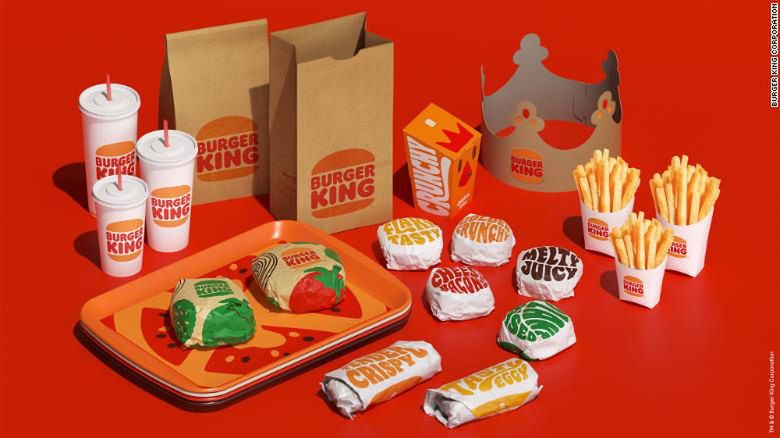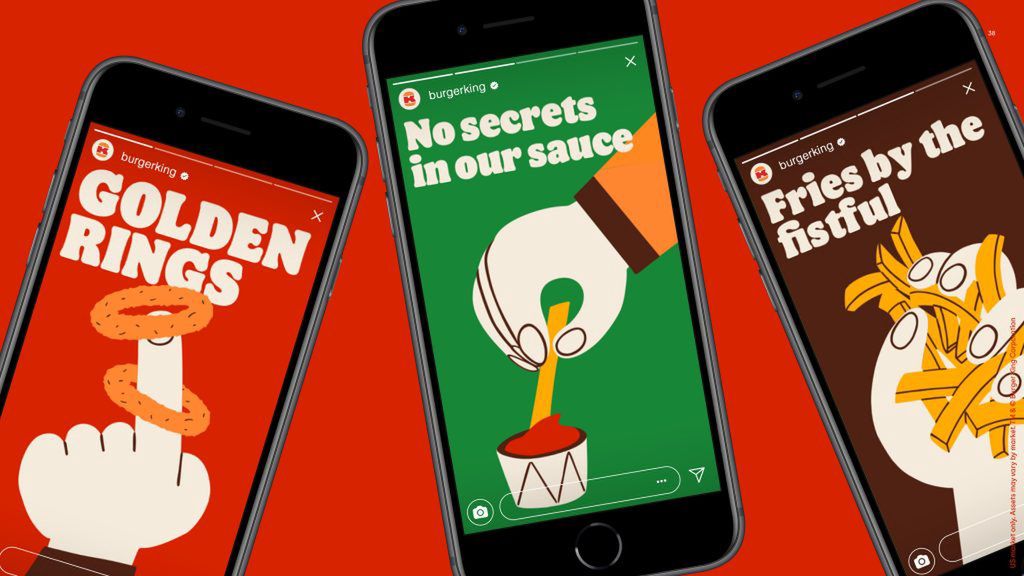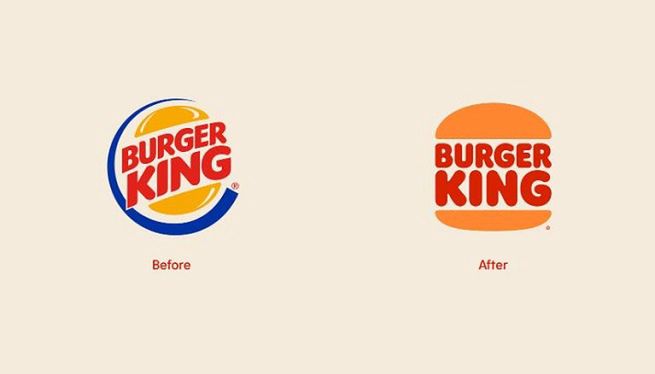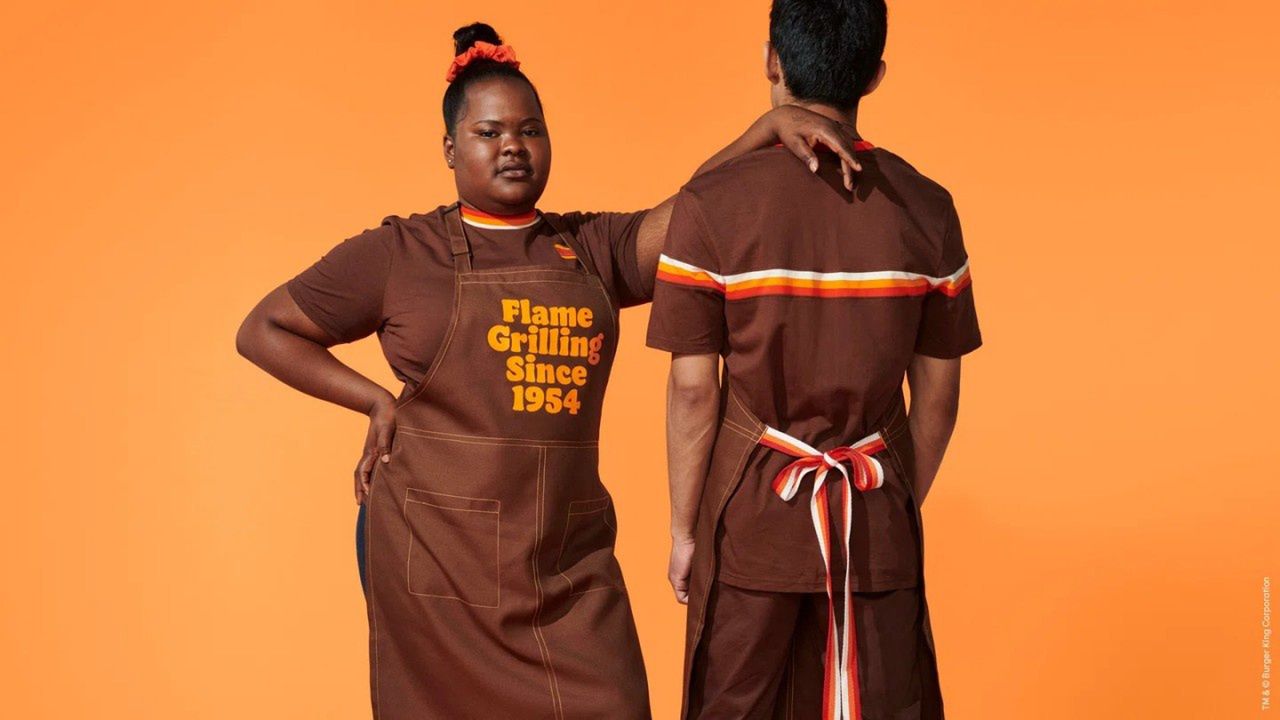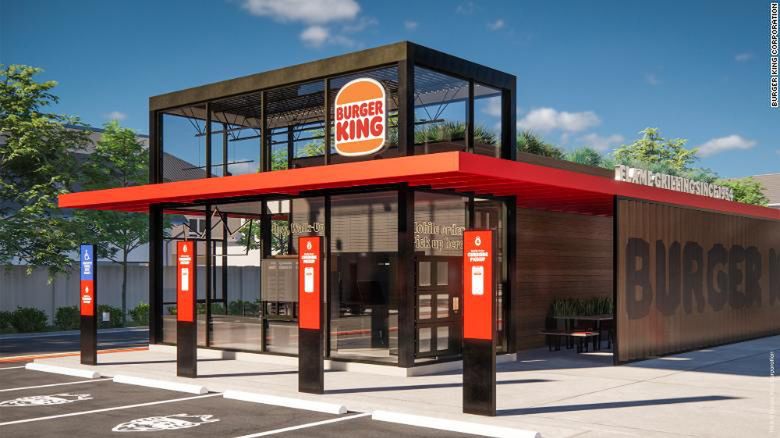
Burger King ma nowe logo. Pierwsza zmiana od 20 lat
Po 20 latach sieć fastfoodów Burger King zmieniła logo. Podkreśla przez to ostatnie zmiany w filozofii marki. Projekt przygotowała agencja Jones Knowles Ritchie.
Kolory zaprezentowanego w czwartek nowego logo są wedle Burger Kinga "inspirowane prawdziwym i pysznym jedzeniem". W nowej wersji rezygnowano z niebieskiej obwódki na rzecz symbolu burgera, pozostawiono zaś wypisaną czerwonymi literami nazwę brandu.
W nowej identyfikacji pojawił się niestandardowy krój czcionki (częściowo szeryfowy), nazwany Flame.
Nowe logo Burger Kinga
- Minimalistyczne logo płynnie wpisuje się w ewolucję marki w dzisiejszych czasach - wyjaśniają przedstawiciele marki w komunikacie.  Nowa identyfikacja podkreśla, że Burger King poprawił jakość oferty, eliminując ze składów burgerów konserwanty. - Zrobiliśmy wiele, żeby poprawić jakość jedzenia - komentuje Fernando Machdao, globalny szef marketingu firmy Restaurant Brands International, do której należy Burger King.
- Chcieliśmy wykorzystać design, aby zlikwidować lukę między negatywnym postrzeganiem fast foodów przez ludzi a pozytywną rzeczywistością historii kulinarnej. Chodziło nam o sprawienie, by marka wydawała się mniej syntetyczna, sztuczna i tania, a bardziej realna, pożądana i smaczna - dodaje Lisa Smith, executive creative director agencji Jones Knowles Ritchie, która przygotowała projekt.
Jak podano starano się to uzyskać na kilka różnych sposobów. Twórcy identyfikacji odeszli od syntetycznego logo z 1999 r., z okrągłym niebieskim obrysem ikony burgera. Smith i jej zespół zastąpili ten znak zaktualizowanym riffem w wersjach z 1969 i 1994 r. To stonowany, prosty, płaski kreskówkowy burger z napisem „Burger King” wciśniętym między połówki bułki.
Nowy projekt zawiera też zabawne ilustracje hiszpańskiego duetu Cachetejack. Projekty te mają stwarzać Burger Kingowi nowe możliwości oznaczania wszystkiego: od komunikatów o błędach na stronie internetowej, przez reklamy cyfrowe i grafiki społecznościowe, po papier do wykładania tac w lokalach. Kreskówkowe postaci obracają krążki cebuli, jedzą frytki czy używają plasterków pikli jako lornetki.
Zmiany w Burger King
Nowe logo pojawiło się już na ubraniach pracowników sieci, opakowaniach produktów, a wkrótce trafi do placówek stacjonarnych (są w trakcie przebudowy).
Odświeżenie wizerunku wszystkich 19 tys. restauracji Burger Kinga na świecie może potrwać nawet kilka lat.